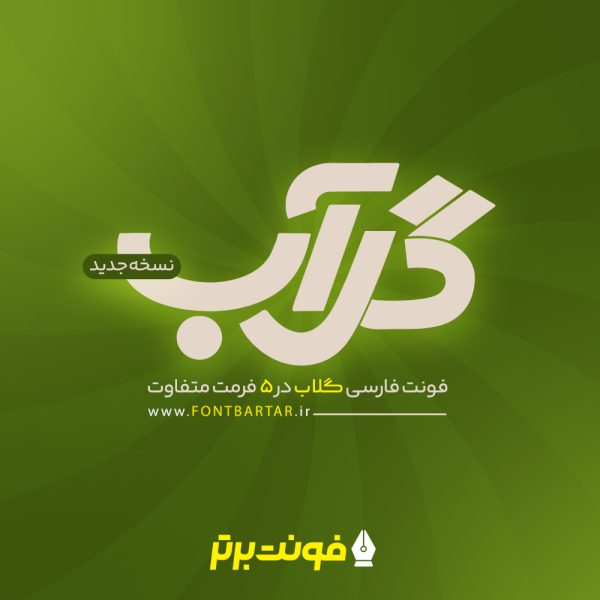
فونت فارسی گلاب
فونت فارسی گلاب یک فونت بسیار زیبا و شاد که تا مدتها میتواند نیاز شما به یک قلم اصلی برای کارهای تیتر و توضیحی و غیره بر طرف کند. این قلم را میتوانید در کارت ویزیت ، پوستر ، تابلوهای سردرمغازه ها ، کارهای تبلیغاتی و غیره به راحتی استفاده نمایید .
فونت گلاب به سبکی طراحی شده که می توان در هر مضمونی تایپوگرافی ،لوگو تایپ،تبلیغات محیطی یا در معرفی محصول خاص و… از آن بهره برد فونت گلاب پتانسیل ویرایش را نیز دارد شما می توانید با کمی خلاقیت در نرم افزار های فتوشاپ یا ایلوستریتور از این فونت طرح های خلاقانه و زیبا اجرا کنید.
فونت گلاب دارای چند وزن است؟
- این فونت در یک وزن می باشد.
فونت گلاب از چه زبان هایی پشتیبانی می کند؟
- از یک زبان فارسی را پشتیبانی می کند.